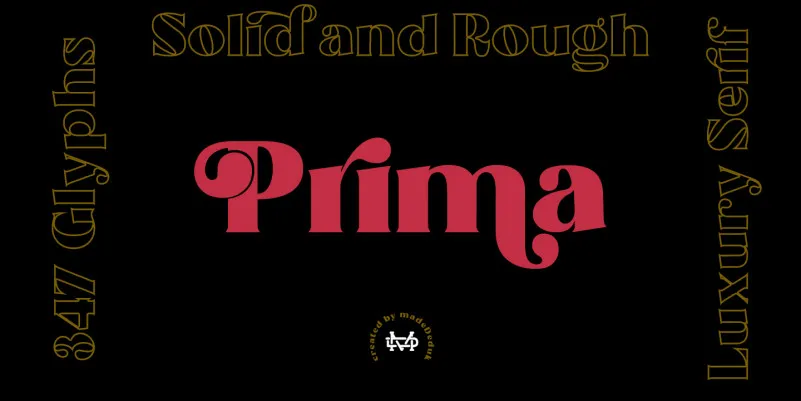
Prima é uma fonte tipo luxuoso que inclui ligaturas e alternativas para cada característica. Esta fonte não só oferece versões rústicas e solidas, mas também muitas alternativas estilizadas de caracteres, tornando-a perfeita para qualquer projeto de design. MadeDeduk é o designer responsável pela criação desta elegante fonte que traz uma atmosfera sofisticada e aconchegante. Com Prima, você terá um recurso adicional para dar seu trabalho de design aquele toque final de luxo e sofisticação. Seja em um site ou em um projeto de impressão, Prima é perfeito para criar um visual impecável que destaca sua criatividade e estilo único. Sempre uma excelente escolha para aqueles buscando um tom elegante e requintado.